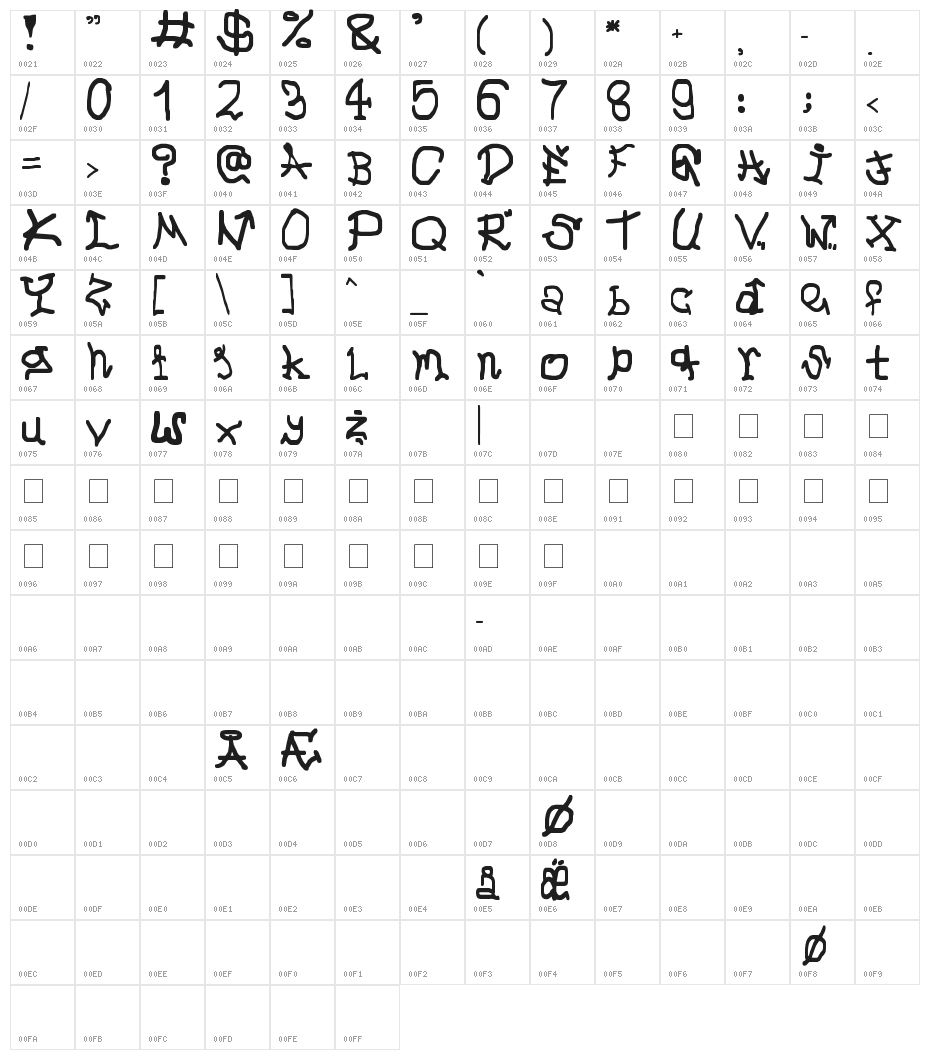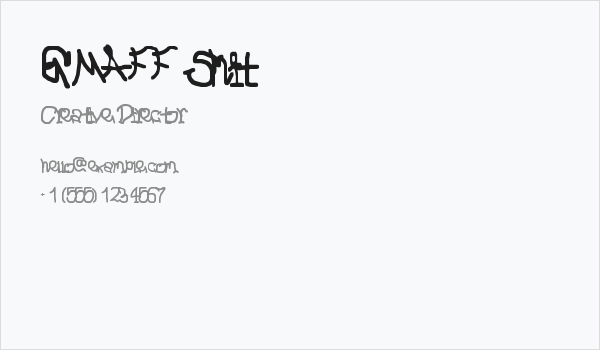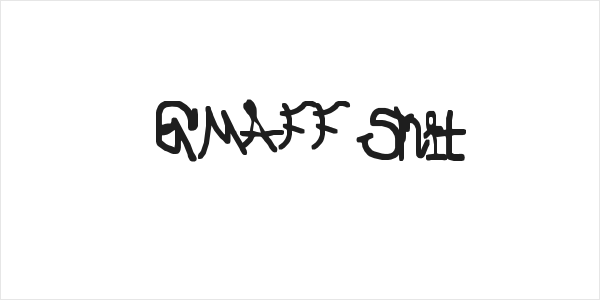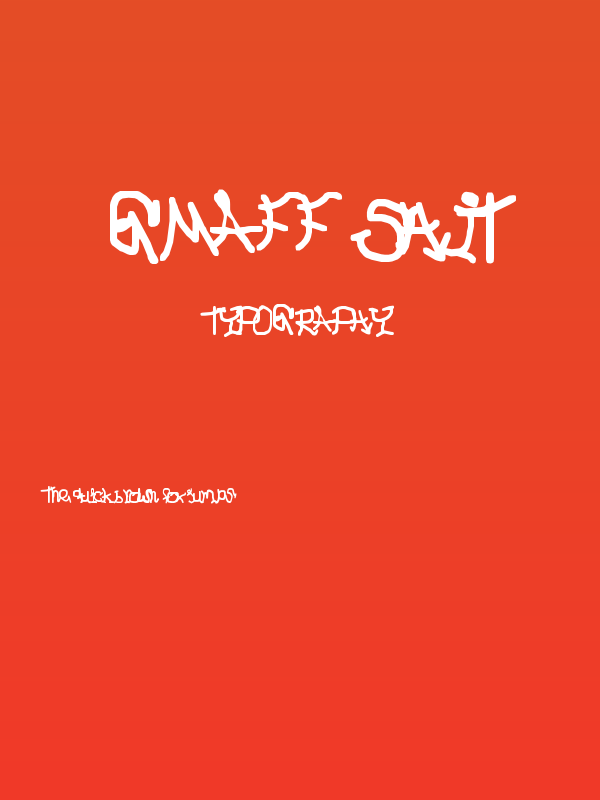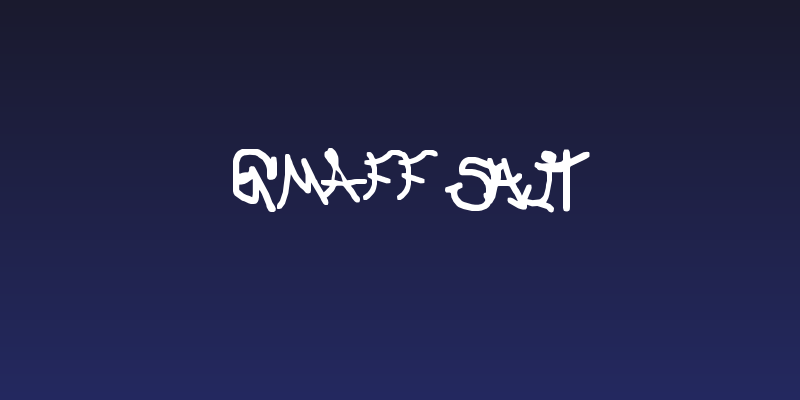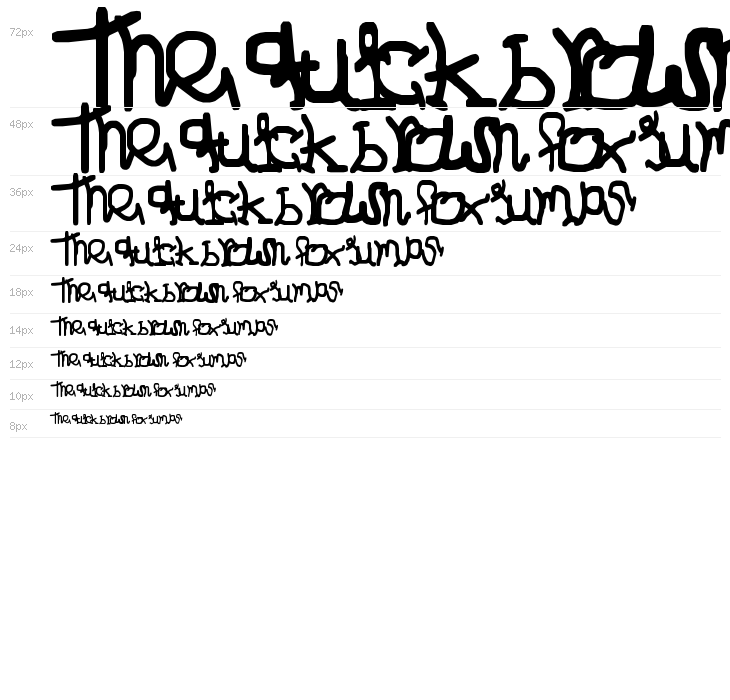
GMAFF Shit Font
| Caso d'uso | Logos, Artistic designs, Posters |
| Progetti proposti | Ideal for street art designs, edgy posters, album covers, and any project requiring a bold, artistic statement. |